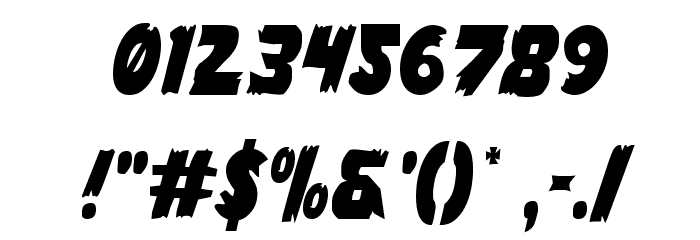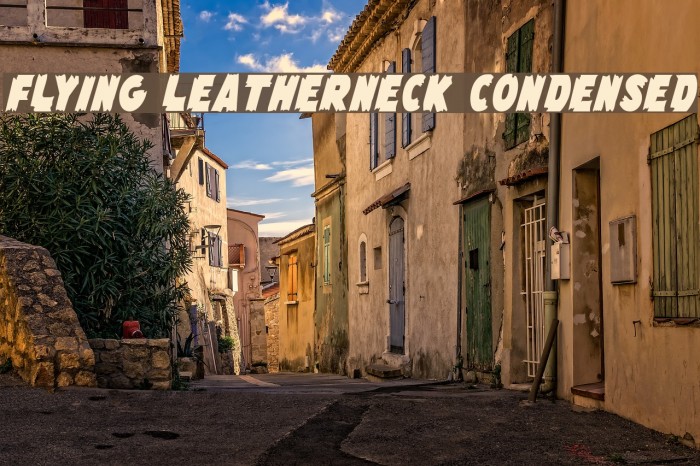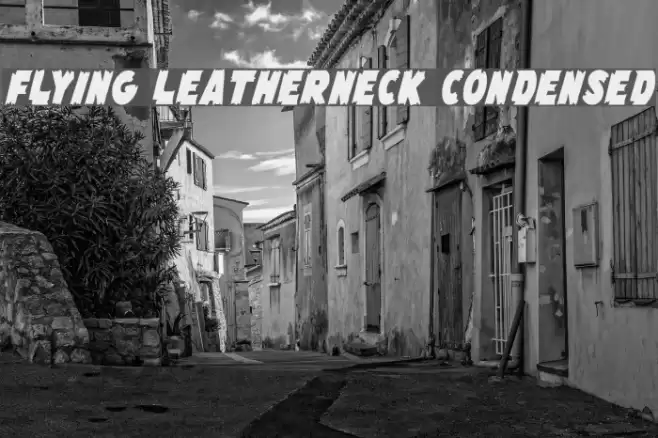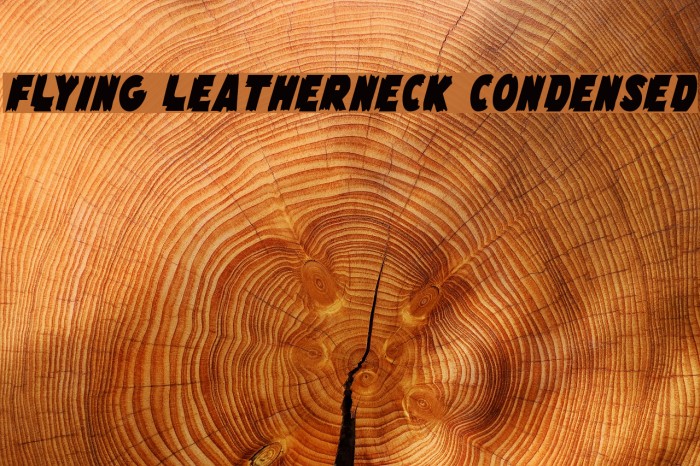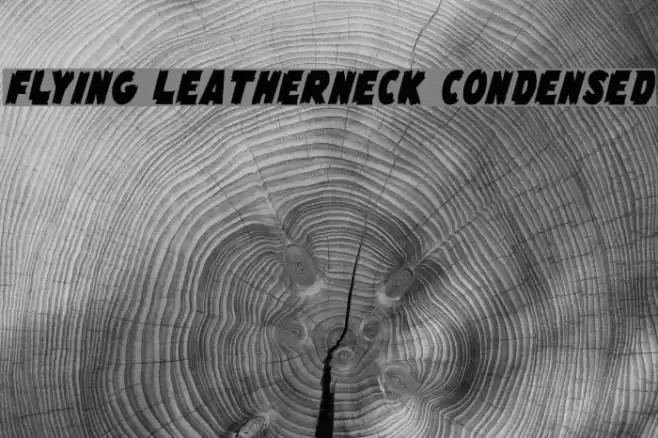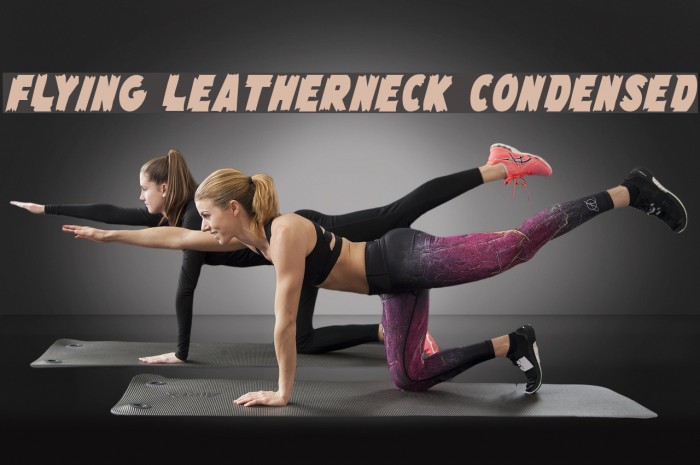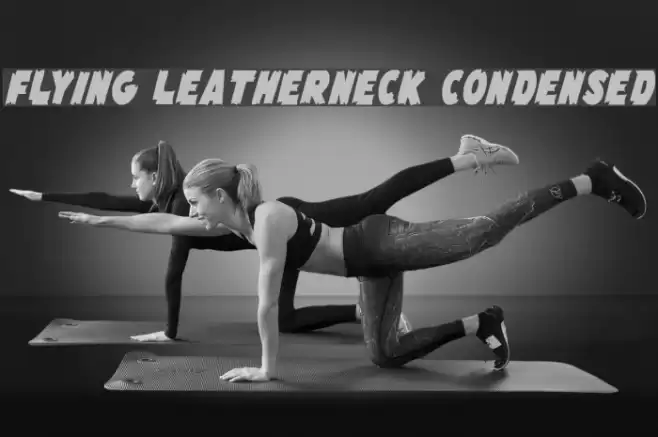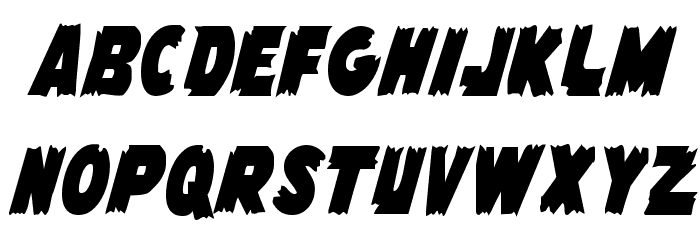
Flying Leatherneck Condensed Font
| Estilo geral | Modern, Energetic |
| Projetos propostos | Ideal for sports branding, action movie posters, video game titles, and dynamic event flyers. |